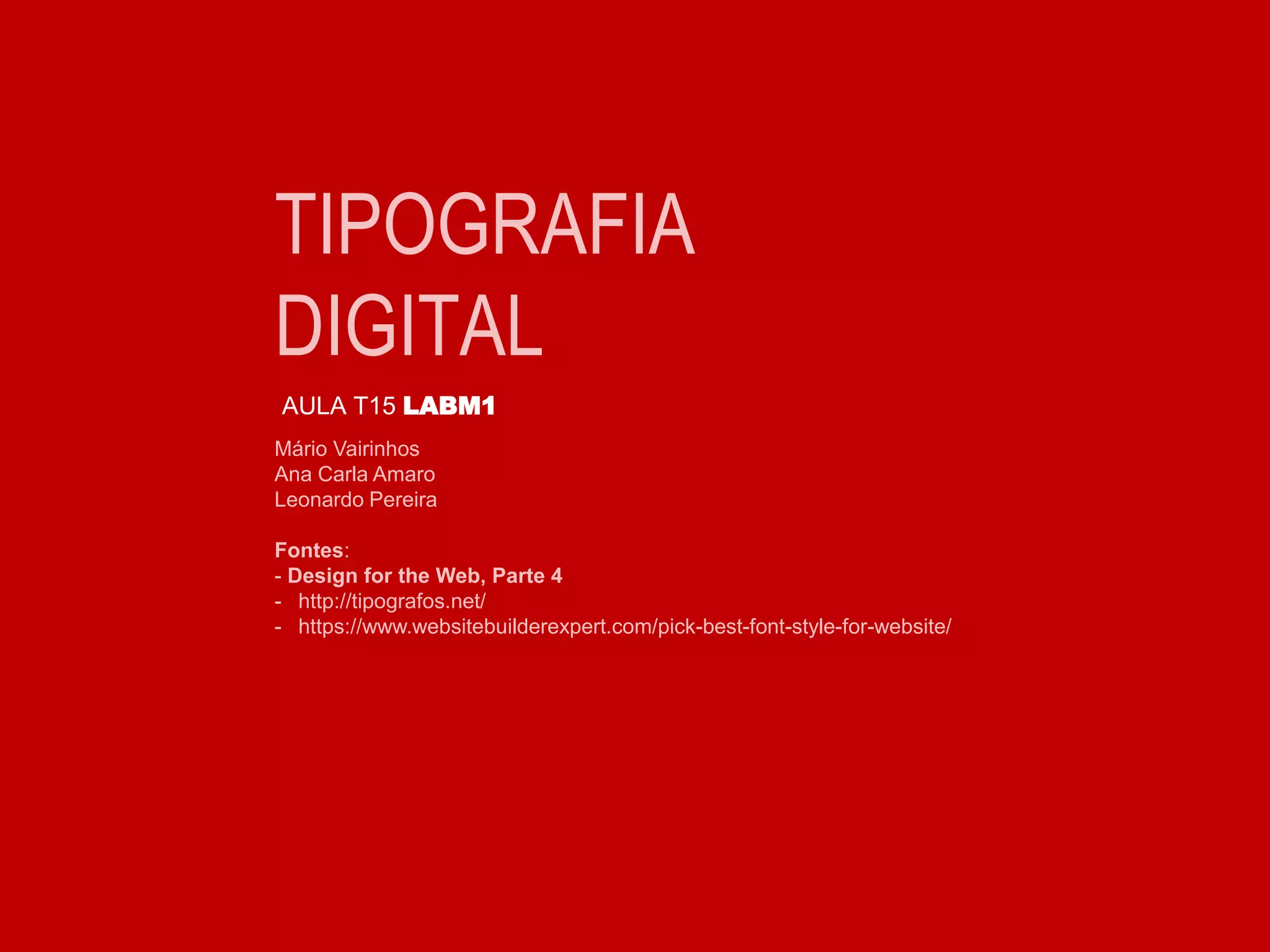
TIPOGRAFIA
DIGITAL
AULA T15 LABM1
ESPAÇAMENTO E PARÁGRAFO
- Espaçamento entre linhas (Leading)
- Espaçamento entre caráteres (Kerning)
- Espaçamento entre proporcional entre caráteres (Tracking)
- Espaçamento entre palavras (Word Spacing)
LEADING
ESPAÇAMENTO ENTRE LINHAS
A proveniência do termo remonta ao tempo em que os
tipos eram constituídos por metal (chumbo, lead na
língua inglesa). O tipógrafo modulava o espaço entre as
linhas introduzindo tiras estreitas de metal (chumbo)
entre cada uma das linhas.
Consiste na distância entre as linhas de base
(baselines) entre duas linhas de texto e pode ser
expresso em px, pt, cm ou ainda em percentagem da
dimensão da fonte, o corpo (distância entre a linha de
base e a linha das ascendentes).
LEADING
ESPAÇAMENTO ENTRE LINHAS
O espaçamento entre linhas produz não apenas um
forte impacto visual como também na dimensão do
próprio texto. Este impacto é maior do que a própria
dimensão da letra (corpo). Por essa razão, quando se
pretendete ajustar a dimensão do texto numa caixa ou
numa página, o leading produz a maior variação.
As fontes necessitam de diferentes espaçamentos entre
linhas de modo a se obter o mesmo efeito visual.
Geralmente, fontes com altura-X elevada relativamente
à linha das ascendentes necessitam de mais
espaçamento entre linhas para ter a mesma
legibilidade. Este efeito é mais evidente quando o texto
é apresentado a corpo pequeno. No exemplo ao lado, a
fonte do parágrafo superior tem uma altura-Z mais
elevada que a do inferior.
LEADING
ESPAÇAMENTO ENTRE LINHAS
O espaçamento entre linhas afecta sobretudo a coesão
do texto como um todo e o seu subsquente
agrupamento perceptivo. Quanto maior é o leadin,g
maior o ênfase visual que, individualmente, cada uma
das linhas adquire, e, inversamente, menor é o
agrupamento visual do texto (conjunto de linhas).
A partir de um certo valor de leading o texto perde a sua
coesão e deixa de ser percepcionado como um
elemento visual.
LEADING
QUAL O VALOR ADEQUADO?
120% ?
Não existe um valor certo, absoluto, que optimize a
legibilidade do texto. De facto, a legibilidade e o valor
do leading adequado para um fonte depende um
variado número de factores, desgnadamente:
o corpo, a altura-x, o estilo da fonte, o contraste do
traço, a largura e até mesmo os atributos aplicados ao
texto, tal como a tonalidade cromática, a saturação e o
contraste de luminosidade.
Contudo, em termos médios é convencionalmente
aceite um valor para o leading de 120% relativamente
à dimensão do corpo. Assim, se uma fonte for aplicada
com 10pt de corpo o espaçamento entre linhas deverá
ser de 12pts (ou 120% de 10pt).
O Adobe Photoshop, o Adobe Illustrator e o Adobe
Indesign têm predefinidos para a opção automática do
leading o valor de 120%.
Este número (mágico) deverá ser encarado como um
ponto de partida para a escolha do leading e não
como uma imposição de natureza absoluta.
KERNING
ESPAÇAMENTO ENTRE PAR DE LETRAS
Kerning é o processo de adicionar ou subtrair espaço
entre um par de letras em particular.
Nem todas as letras do alfabeto ficam bem com o
mesmo espaçamento. Por exemplo, a distiância entre a
letra a e a letra W ou V deve ser encurtada quando
comparada com outras combinações, por exemplo a
letra a e i.
TRACKING
ESPAÇAMENTO PROPORCIONAL ENTRE
LETRAS
Kerning é o processo de adicionar ou subtrair espaço
entre às letras de um bloco de texto (e não a pares de
letras em particular)
O Tracking afecta visualmente a densidade do texto e
consequentemente a legibilidade do texto.
Quando o corpo de texto é de reduzida dimensão torna-
se necessário adequar com um valor de tracking mais
elevado como forma de assegurar a legibilidade do
texto. Ao adicional espaço negativo em redor das letras
estas torna-se mais facilmente reconhecidas e
percepionadas pelo utilizador.
Quanto menor for o tracking maior a coesão visual da
palavra, inversamente, quanto maior o tracking menor a
força do agrupamento visual da palavra.
CRITÉRIOS PARA ESCOLHA DEUMA FONTE A fonte pertence a uma família que proporciona todos os pesos e cortes necessários? Aspectos técnicos: será que o set de glifos incluiu todos os diacriticos e sinais de pontuação necessários? Aspectos funcionais: legibilidade, que é a usabilidade das letras (design das letras, formas características, espaçamentos) Estética, relação entre os diferentes caráteres e cortes. Relacão com outras fontes utilizadas no mesmo documento. Aspectos de concordância (romano e itálico de uma mesma fonte) Fonte: http://tipografos.net/glossario/escolha-de-fontes.html http://letritas.info/15-tips-al-elegir-un-buen-tipo-de-texto/